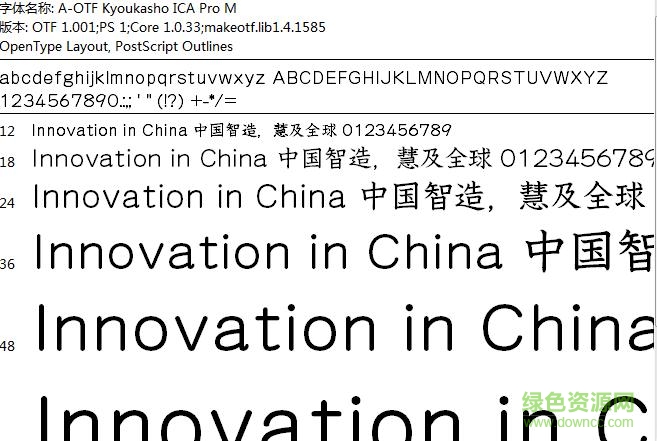
日文教科書體是專為需要使用各種字體的朋友準(zhǔn)備的一款日本中文字體,整體效果融合工整,沒有一絲多余的筆畫,非常的醒目,有需要的朋友歡迎下載使用!
日文教科書體是一款日系中文字體,是根據(jù)日本教科書中的字體打造而來,筆畫簡潔、筆鋒柔和典雅,曲線舒展,剛?cè)岵?、工整而不失精巧,最大程度的展現(xiàn)筆畫的柔和秀美,濃筆重彩,有極強的視覺表現(xiàn)力。